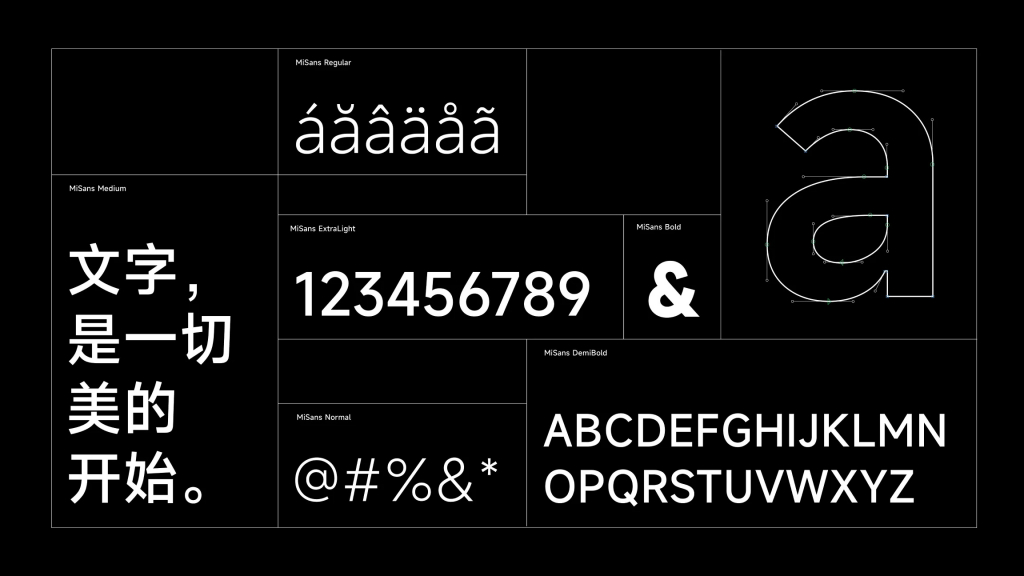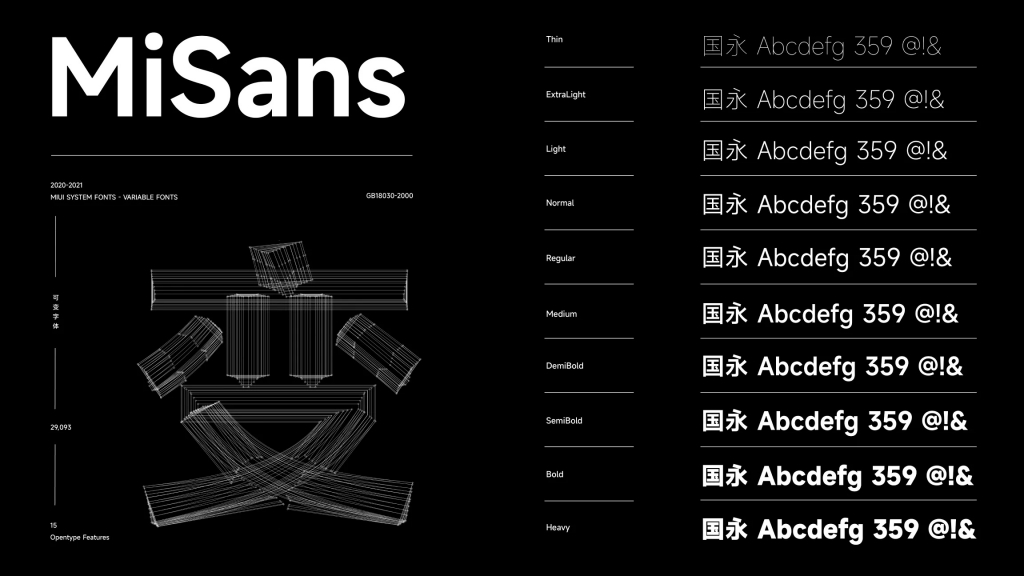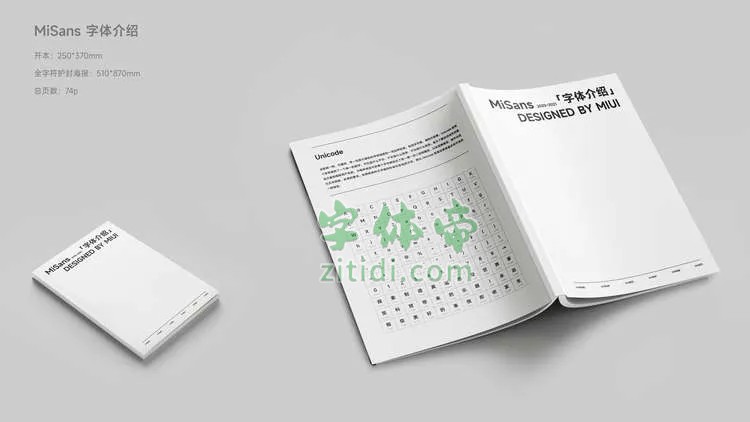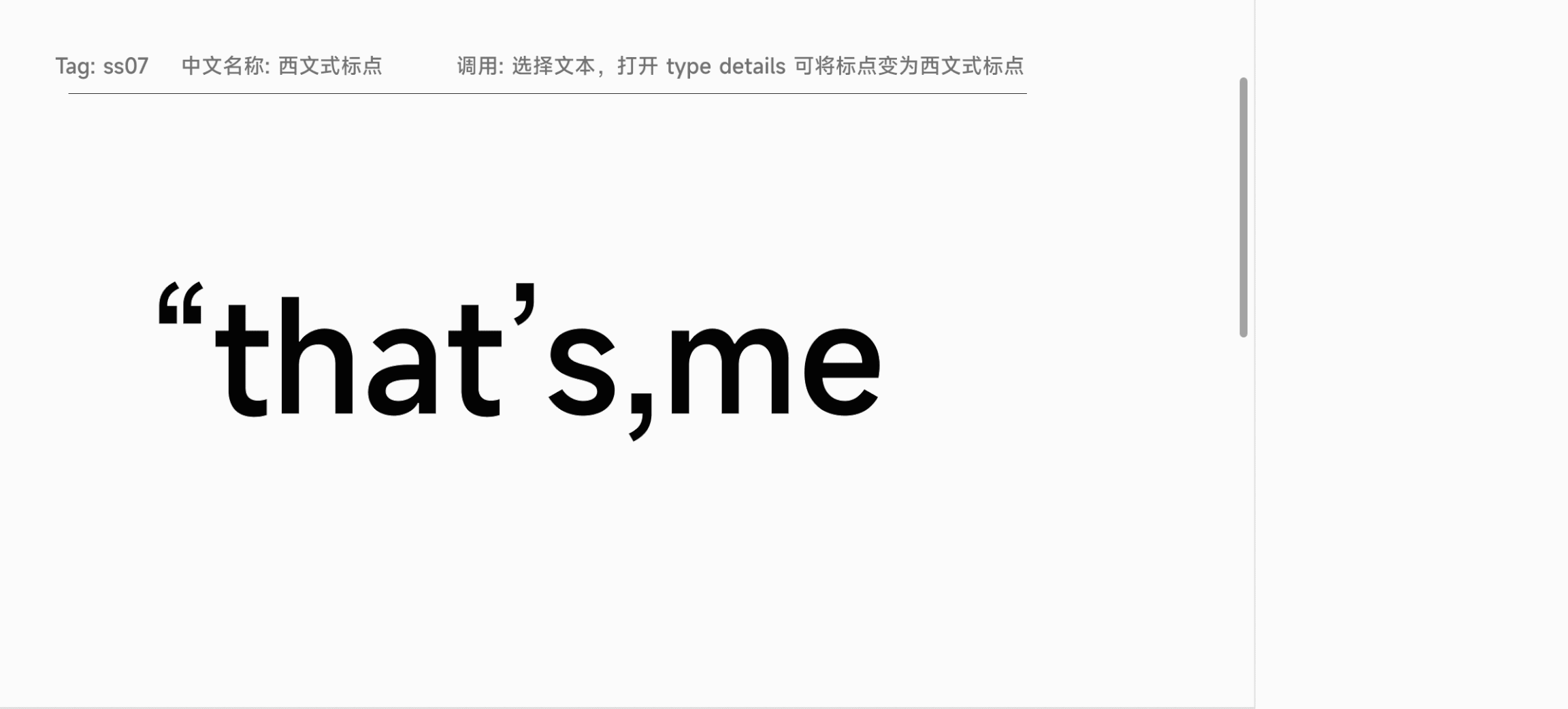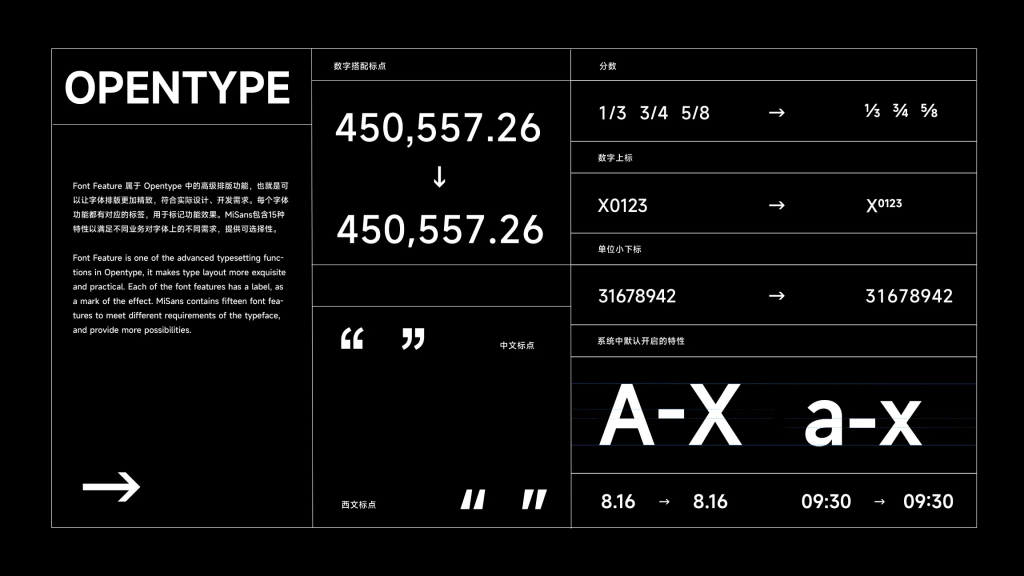
MIUI 13 采用全新系统字体 MiSans; 笔型平直有力,设计更加简约,减少视觉负担,更有利于屏幕显示。共包含29,093个字符,支持多种语言。MiSans 提供了多种 OpenType 功能,可根据特定需求来选择不同形态的字符,例如某些标点符号可以根据周围字母的形态自动调整至合适的位置。MiSans字重齐全,层级清晰,10个字重全部开放下载,供全社会免费商用。
字体展示
字体功能调用及实现
font-feature 属于 Opentype 中的高级排版功能,也就是可以让字体排版更加精致,符合实际设计、开发需求,可根据特定设计需求选择不同的字体形态。大部分软件都可以通过 Opentype 面板访问此功能。 (部分特性在MIUI系统应用中不会默认生效)